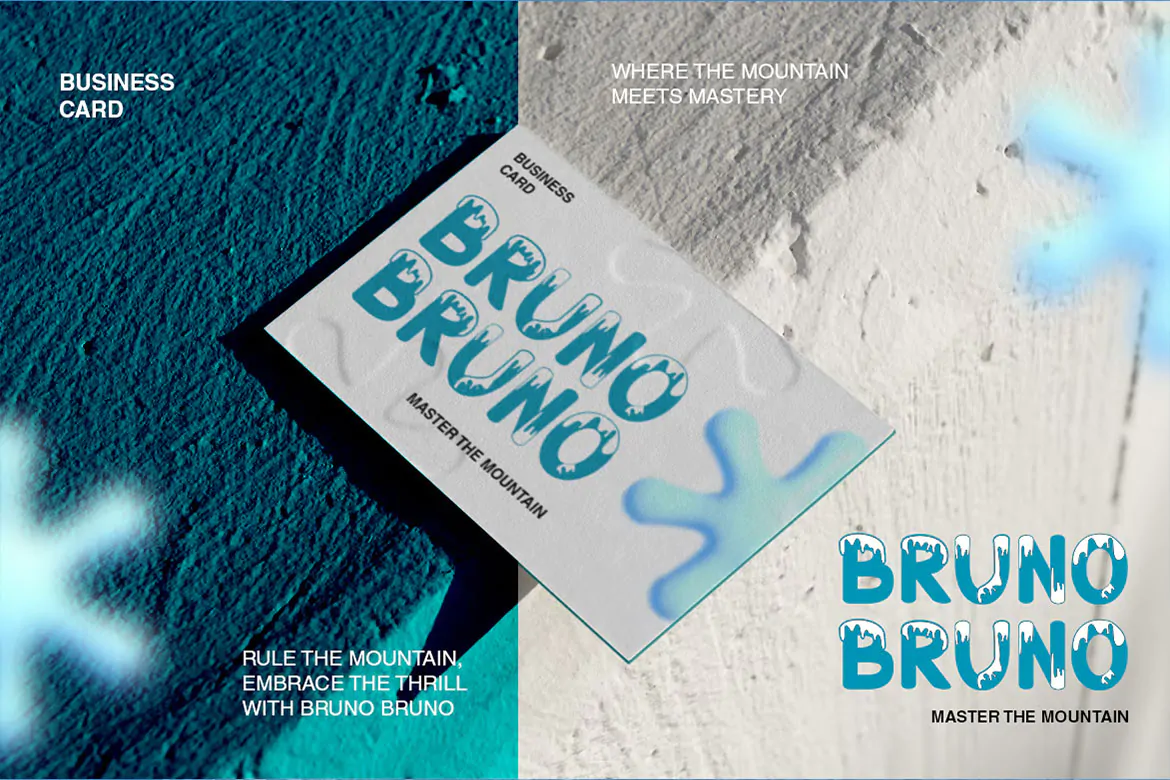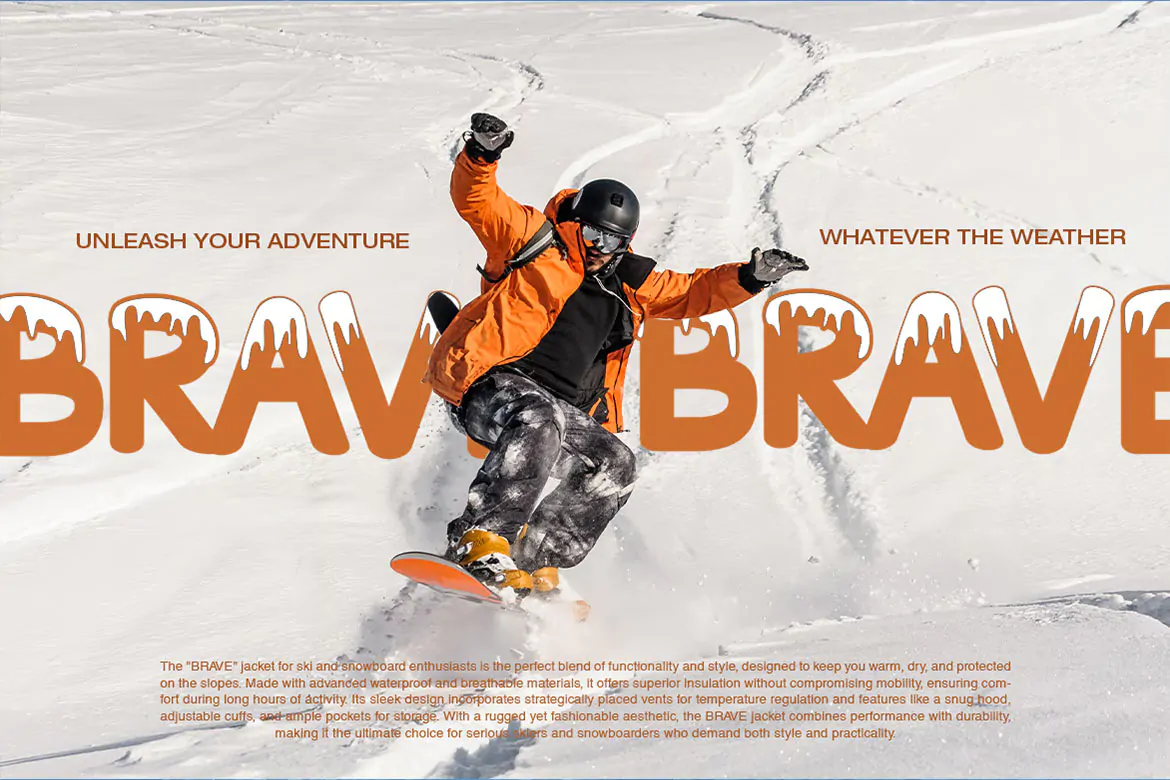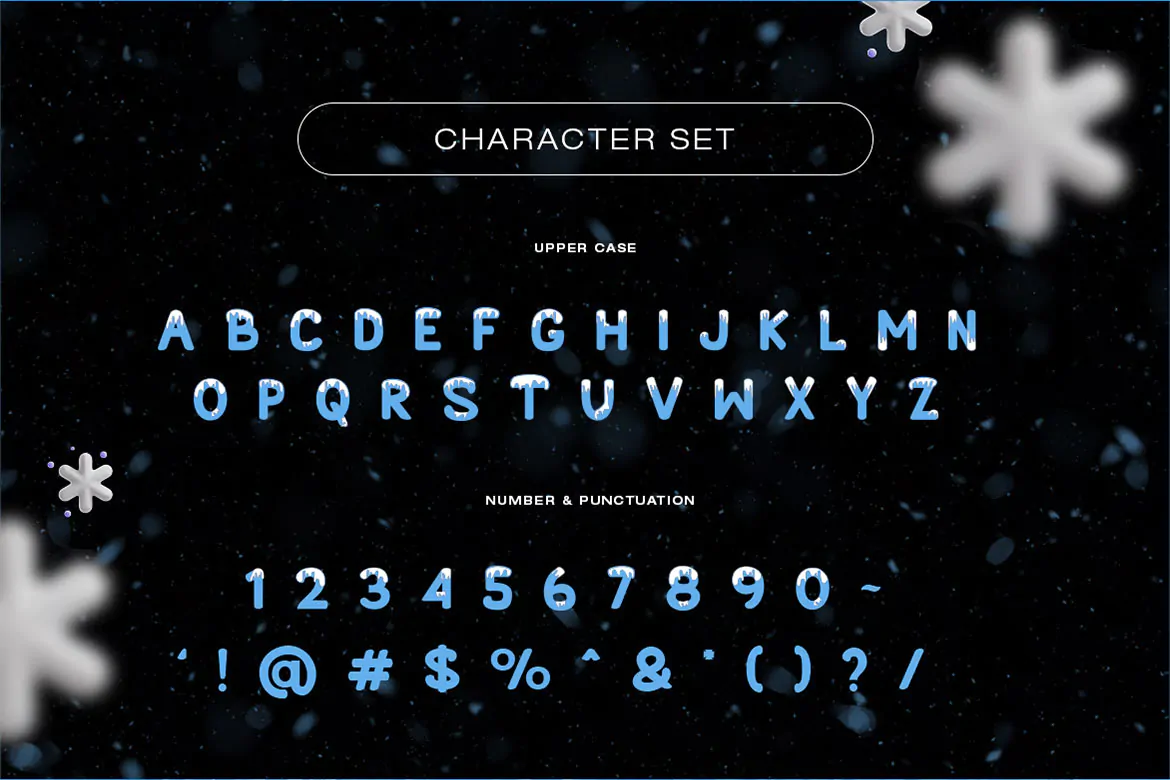
فونت برفی Snowbliss
فونت برفی
فونت برفی Snowbliss یک قلم نمایشی فوق العاده زیبا است که میتوان در طرحهای گرافیکی مختلف همچون طراحی پوستر از آن استفاده نمود.
برای تایپوگرافی، پوستر، هویت بصری و محتوای چاپی یا دیجیتال قابل استفاده است.